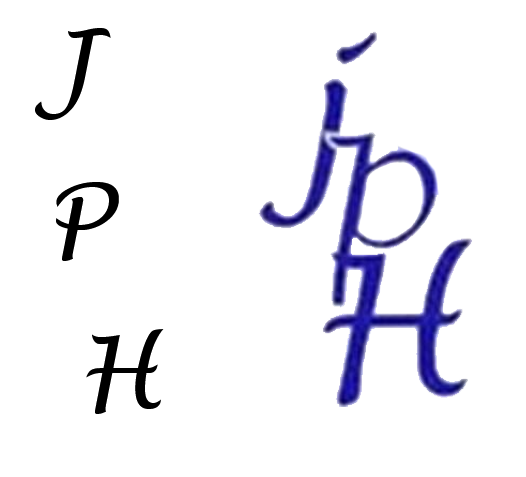
Me font eka mokakda ? download karanna puluwanda ? Link ekak danna pls
redbone Well-known member Nov 24, 2007 1,095 283 83 මඩ ගොඩේ.. Nov 7, 2022 #1 Me font eka mokakda ? download karanna puluwanda ? Link ekak danna pls Reactions: kinkon and Ritigala Jayasena69
signshop Well-known member May 30, 2011 12,301 9,168 113 Dubai Nov 7, 2022 #2 redbone said: Me font eka mokakda ? download karanna puluwanda ? Link ekak danna pls View attachment 188937 Click to expand... Lucida Handwriting Regular https://www.dafontfree.net/lucida-handwriting-regular/f125218.htm Reactions: redbone
redbone Well-known member Nov 24, 2007 1,095 283 83 මඩ ගොඩේ.. Nov 7, 2022 #3 signshop said: Lucida Handwriting Regular https://www.dafontfree.net/lucida-handwriting-regular/f125218.htm Click to expand... Thanks But meka nemai H hari anik akuru match wenne na ne Reactions: Ritigala Jayasena69
Nidarshana_k Well-known member Feb 19, 2022 29,986 1 52,084 113 ප*යාගල sorry.com Nov 7, 2022 #5 redbone said: Thanks But meka nemai H hari anik akuru match wenne na ne View attachment 188949 Click to expand... https://fontsgeek.com/fonts/Lucida-Handwriting-Italic Reactions: redbone
signshop Well-known member May 30, 2011 12,301 9,168 113 Dubai Nov 7, 2022 #7 redbone said: Thanks But meka nemai H hari anik akuru match wenne na ne View attachment 188949 Click to expand... මේ Font එක තමයි බන්. j p අකුරු දෙක Simple ගහපන්. H අකුර Capital Reactions: redbone